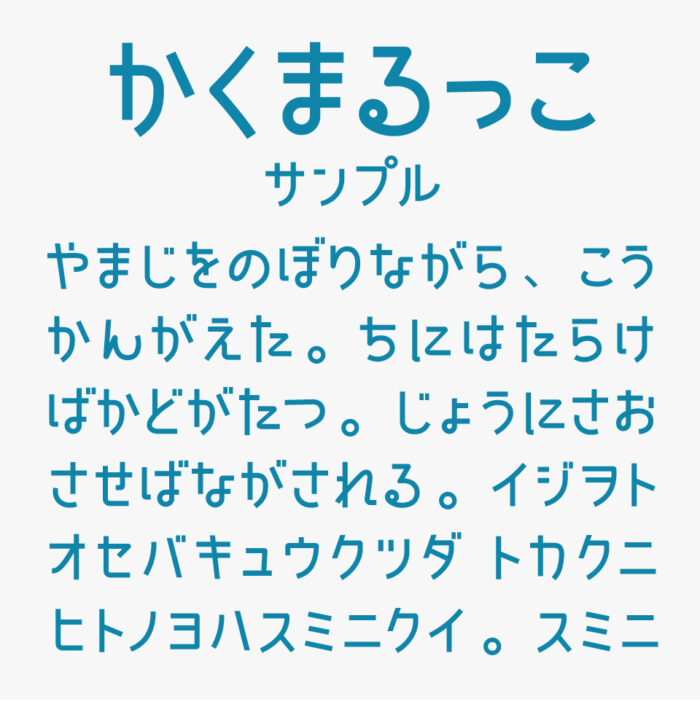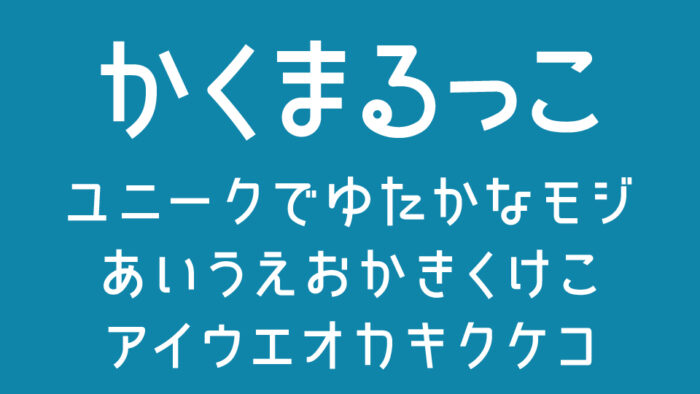
かくまるっこフォントは、カクカクした幾何学的な形の中に、どこかやわらかい丸みを感じさせる可愛らしさ感じるゴシック体フォントです。
丸く処理された角のバランスが絶妙で、可読性を保ちながらも親しみやすさ・やさしさを感じさせる「硬すぎず・可愛くなりすぎず」なちょうどよいデザインです。
収録文字は、ひらがな・カタカナ・記号が収録されています。